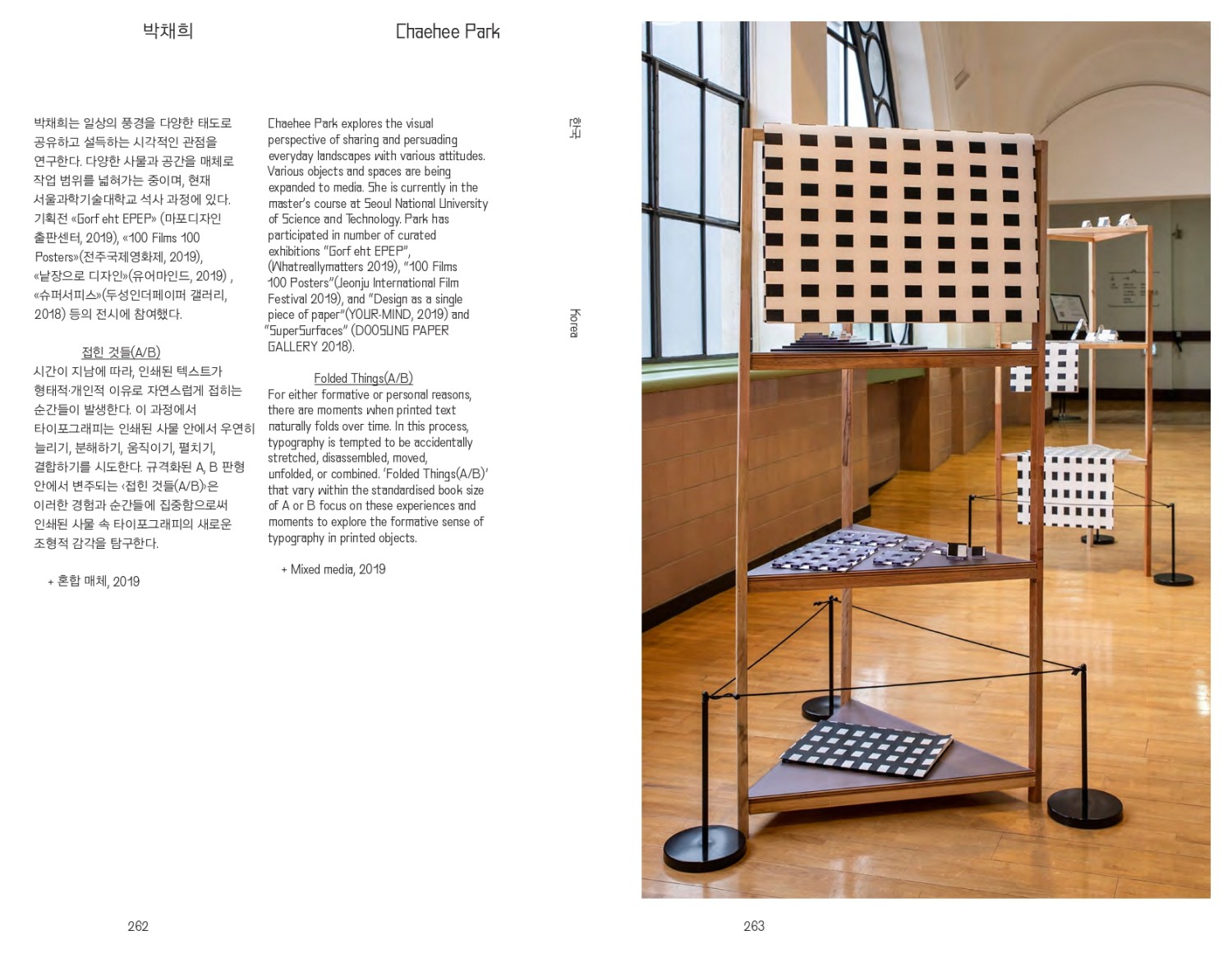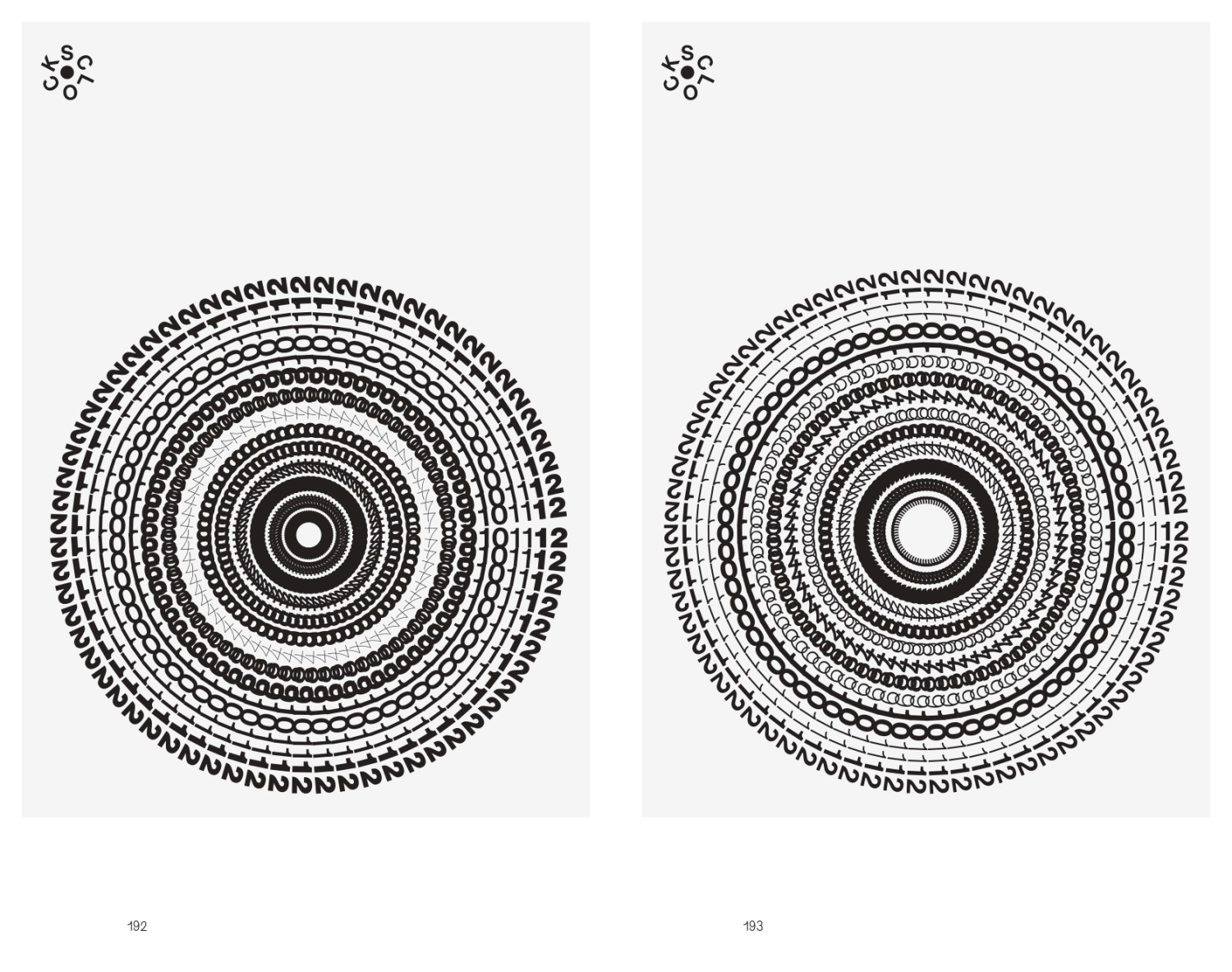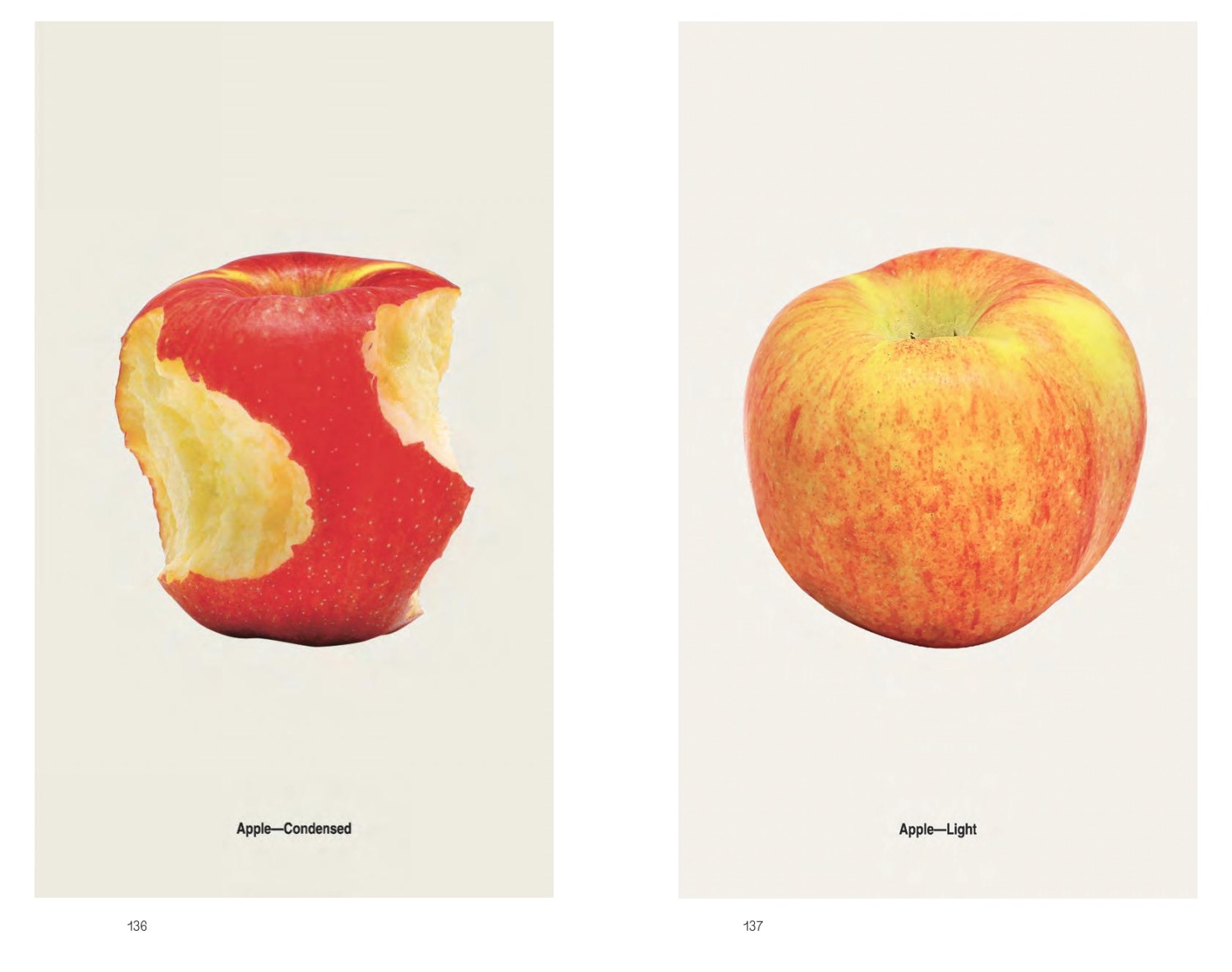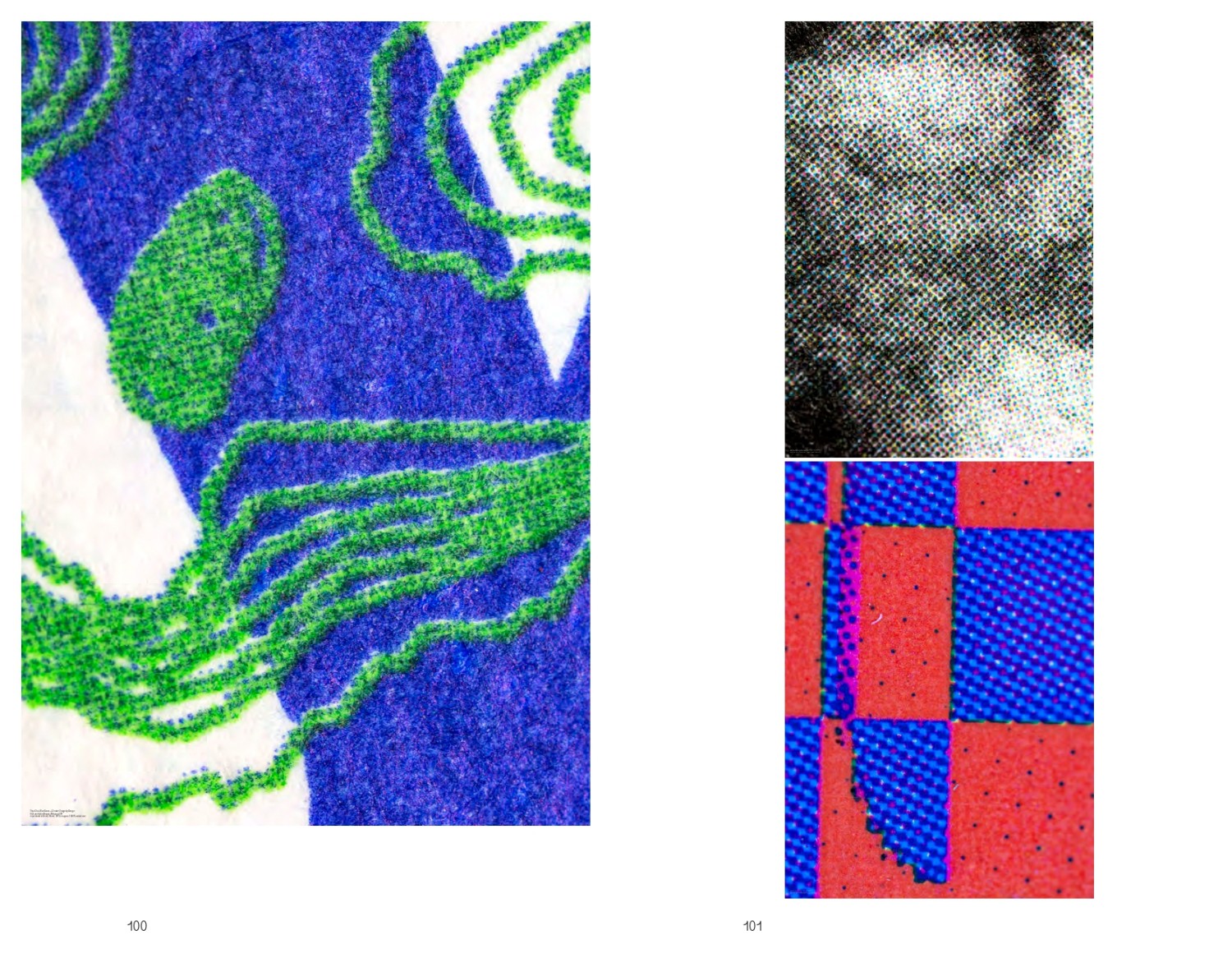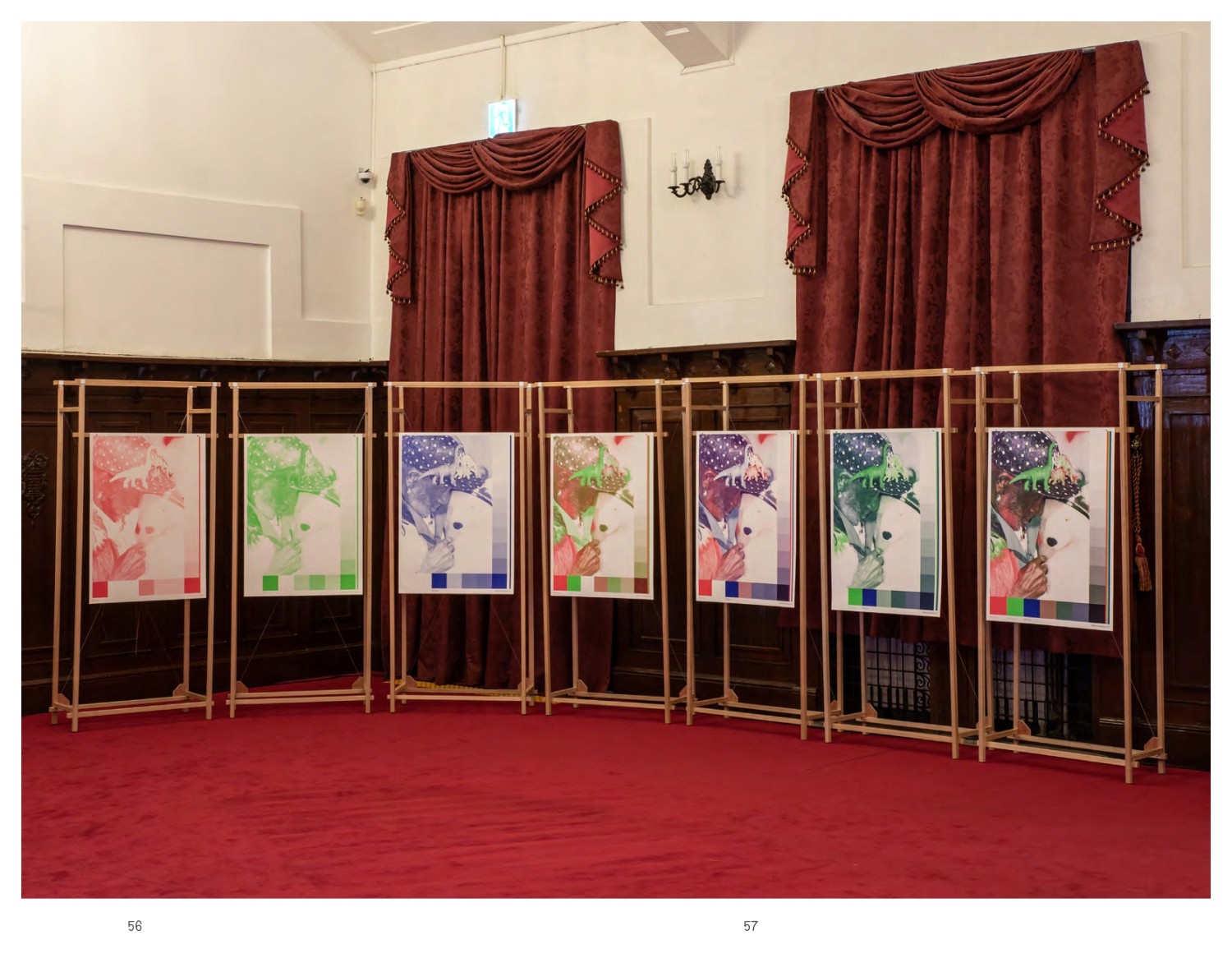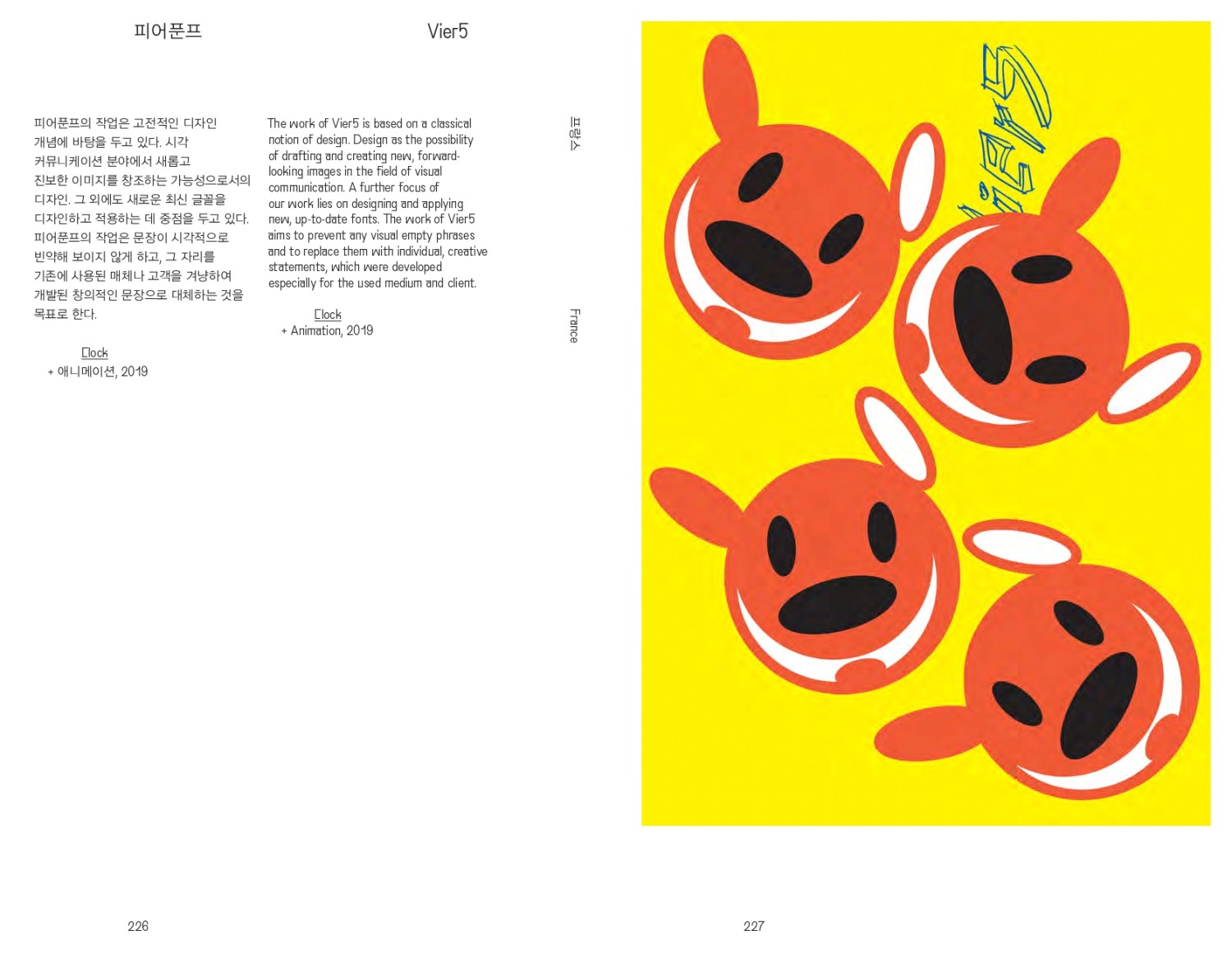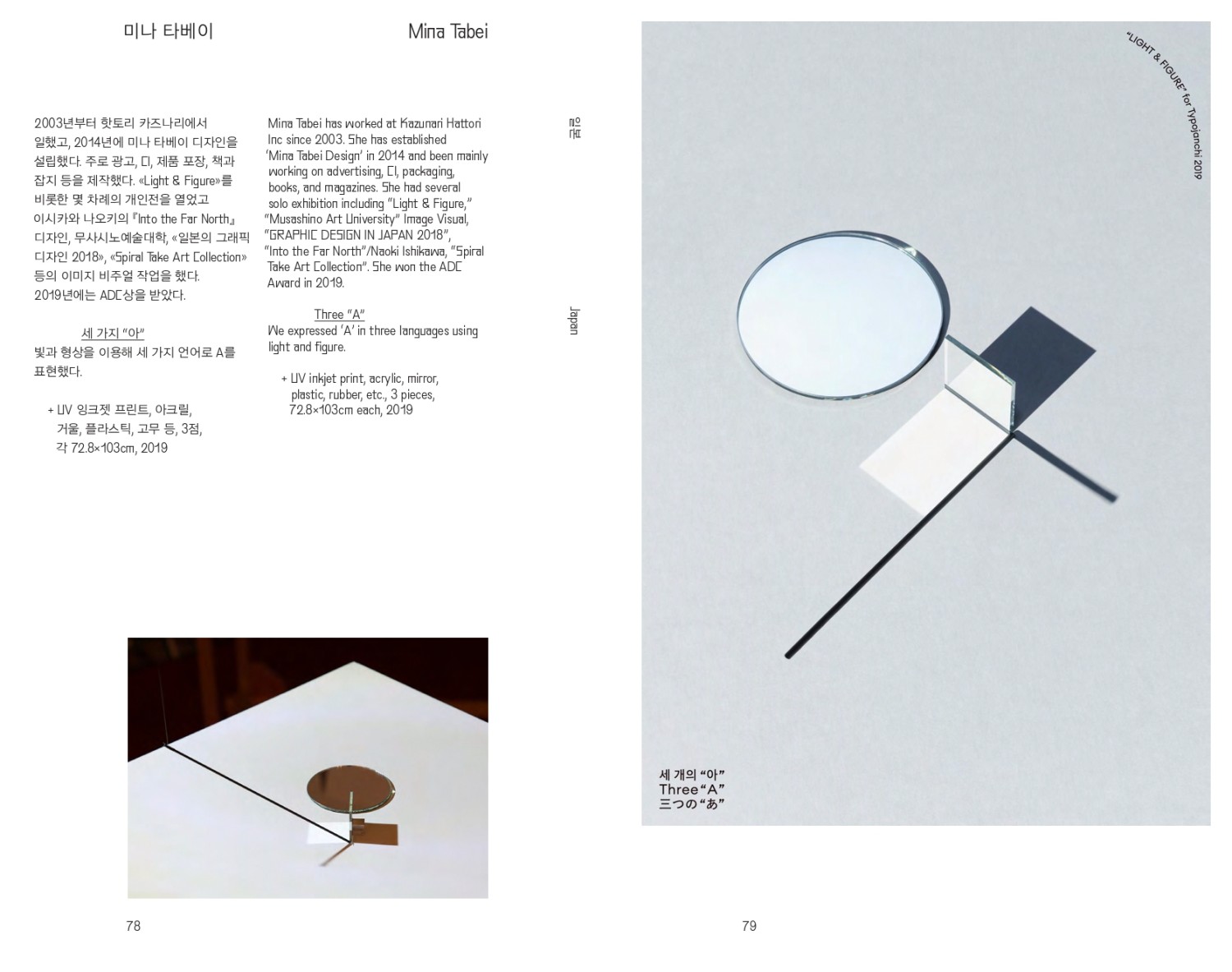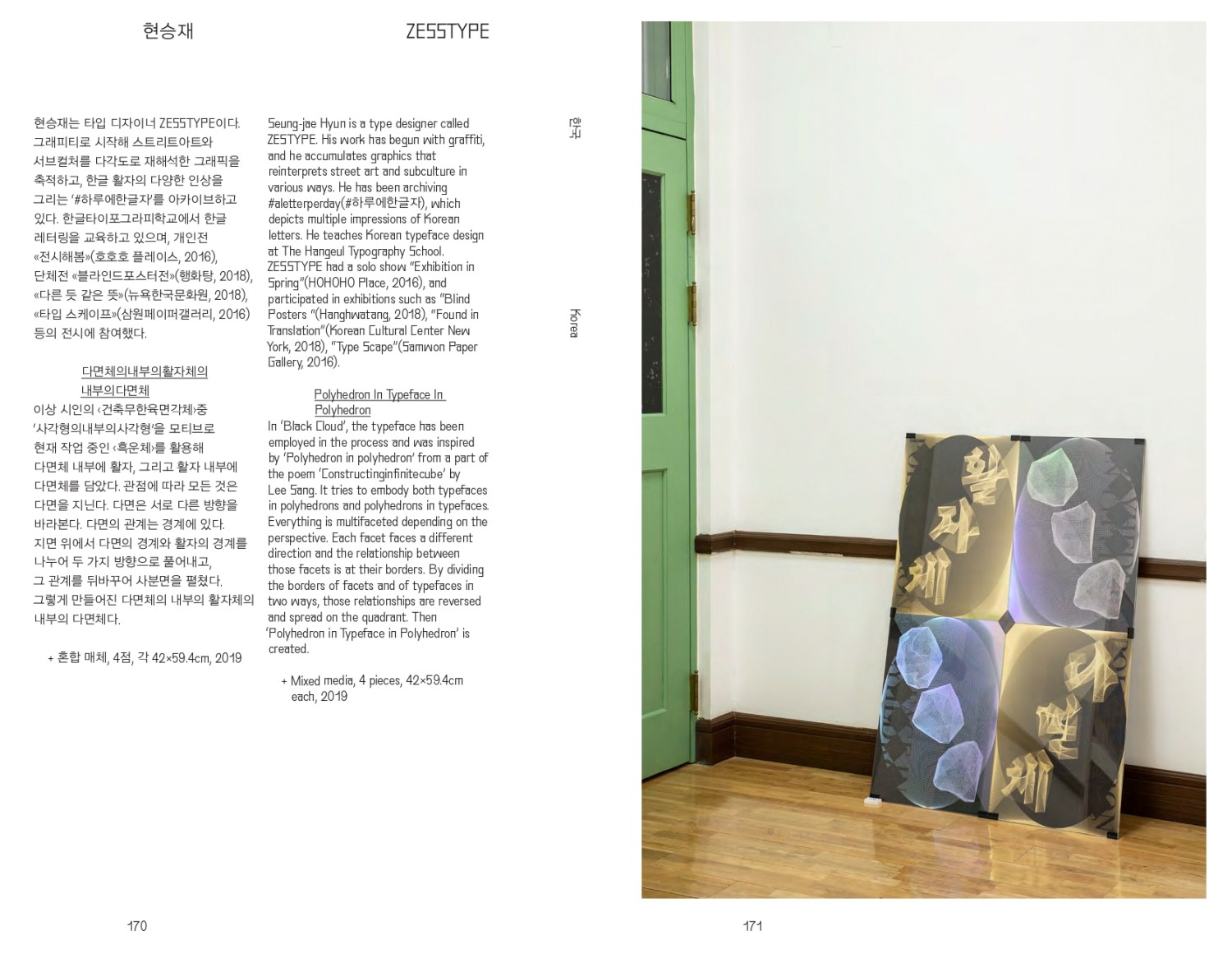
타이포잔치 2019: 만화경과 다면체와 시계와 모서리와 잡동사니와 식물들
- 문자와 사물
- 문화역서울 284 전관
- 2019년 10월 15일 – 2019년 11월 3일
문자가 사물을 닮기 시작했다. 혹은, 사물이 문자처럼 말하기 시작했다. 6회 타이포잔치는 역대 가장 길고 기이한 제목의 전시 《만화경과 다면체와 시계와 모서리와 잡동사니와 식물들》을 통해 ‘문자와 사물’이라는 주제를 유쾌하게 풀어냈다. 문화역서울 284 전관에서 펼쳐진 이번 전시는, 문자와 사물이 맺는 감각적·조형적 관계를 다양한 시선으로 비틀고 탐색하는 실험장이었다. 기자간담회, 본전시, 연계 전시, 토크 프로그램, 출판 등 다층적인 구성 속에서, 22개국 127개 팀(국내 88, 해외 39)의 디자이너들이 사물의 형상과 문자의 리듬 사이를 가로지르며 새로운 언어를 제안했다. 박우혁, 진달래 공동 감독의 기획은, 타이포그래피가 더 이상 고정된 틀 안에 머물지 않음을 증명한다. 활자는 페이지 밖으로 나와 사물과 마주하고, 공간을 점유하고, 감각을 자극하며, 생명력을 얻게 된다. 그 결과, 전시 아이덴티티는 해외 디자인 매거진 ‘2018 올해의 디자인’으로 선정되었고, 타이포잔치는 단순한 비엔날레를 넘어 글자문화의 실험실이자 한글의 아름다움을 알리는 문화 교류의 장으로 자리매김했다. 51,354명의 관람객이 다녀간 이번 전시는, 문자와 사물의 관계를 새롭게 상상하는 계기였고, 동시에 한국 타이포그래피의 국제적 위상을 한층 높이는 전환점이 되었다.